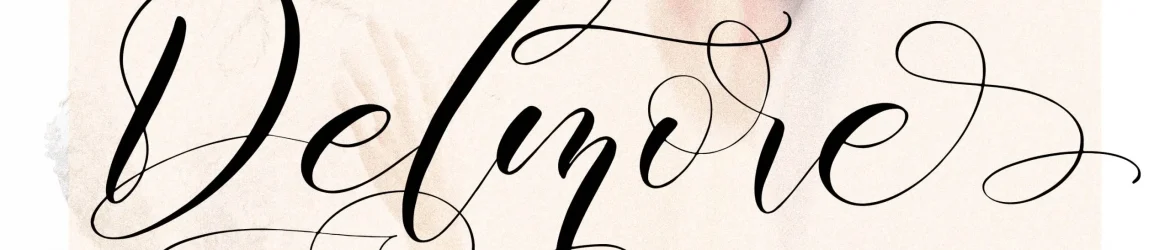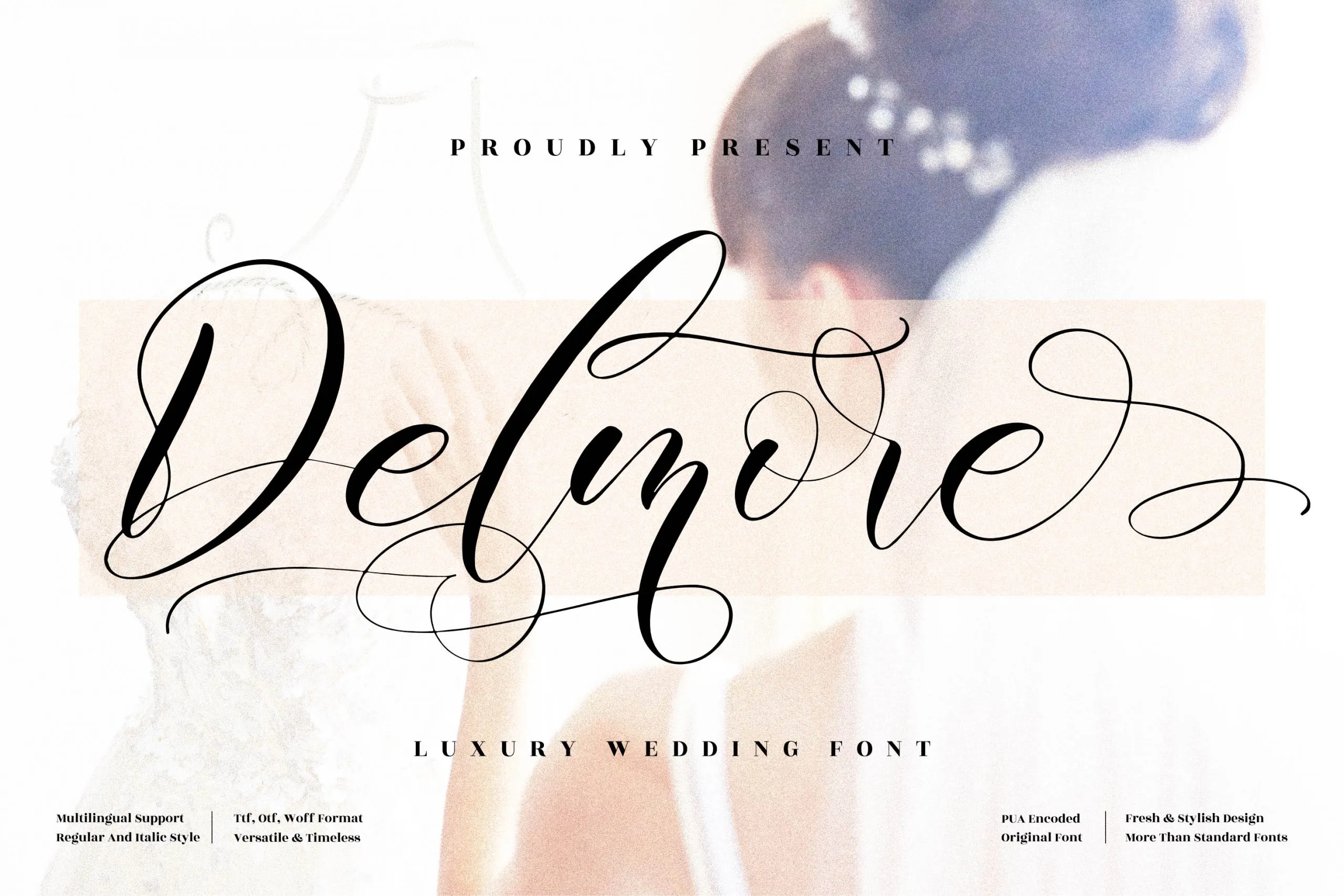
Delmore Font – Fonte Grátis
Delmore Font
A fonte Delmore é perfeita para qualquer projeto que busque uma graça romântica e elegante. Embora tenha sido projetada inicialmente para aplicação em logotipos, marcas de marca e embalagens, a Delmore também cumpre excelentemente sua função como uma fonte serifada, adaptável a diversos produtos do dia-a-dia. Seja em ramos tão variados quanto cháquê, vinil de impressão para camisetas ou até mesmo materiais publicitários, a Delmore está sempre à altura. Além disso, é uma excelente escolha para design gráfico, tais como cartões de nome, convites e mensagens de boas-vindas, capas de livros, etiquetas e mesmo em trabalhos fotográficos ou até mesmo quando você precisa de um toque especial em sua identidade visual. A Delmore pode transformar qualquer projeto, oferecendo um toque de elegância única que tornará seus projetos memoráveis e definitivamente chamativos.